Paragrafzeichen (§)
Das Paragrafzeichen (§) ist eine symbolische Abkürzung für das Wort »Paragraf« (Singular). Paragrafen dienen im allgemeinen der übersichtlichen Gliederung von Gesetzen, Verträgen oder juristischen Publikationen. In der Regel findet das Paragrafzeichen deshalb im dspr. Raum überwiegend Anwendung in Gesetzestexten (z.B. im Bürgerlichen Gesetzbuch) oder in schriftlichen Vereinbarungen (z.B. in einem Vertrag); Allograph »Paragraphzeichen«; symbolische Abkürzung im Plural »§§« für »Paragrafen«.
Das Paragrafzeichen wird ausschließlich in Verbindung mit einer nachfolgenden Arabischen Ziffer bzw. Zahl (ggf. auch Buchstaben) verwendet, die auf den Beginn eines neuen Paragrafen – als eine Art Headline bzw. Subline – oder in Texten (z.B. in einer Klageschrift oder einem Gesetzeskommentar) als Referenz bzw. Konsultation auf einen bestimmten Paragrafen bzw. Absatz in einem Gesetzbuch, Vertrag etc. hinweist (z.B. § 50 Abs. 1 ZPO).
In der Typografie ist das Paragrafzeichen (§) eine Wortligatur, dass zu den Sonderzeichen, hier wiederum zu den Gliederungszeichen zählt. In der Informatik wird das §-Zeichen auch stellvertretend als Platzhalter verwendet, um beispielsweise den Speicherbereich zwischen zwei Adressen von x86 Prozessoren im Real Mode kenntlich zu machen.
Schreibweisen des Paragrafzeichens
Grundsätzlich wird zwischen der Schreibweise in der alltäglichen Textverarbeitung, z.B. in der Bürokommunikation mit Microsoft Word ® oder Pages von Apple ®, HTML-Texten oder mit einer Schreibmaschine, und der Schreibweise im mikrotypografischen Feinsatz mittels professioneller Desktop Publishing Software (DTP), z.B. Affinity Publisher ® von Serif ®, InDesign ® von Adobe ® oder QuarkXpress ® von Quark ®, unterschieden.
Paragrafzeichen mit oder ohne Leerzeichen?
In der alltäglichen Textverarbeitung gelten grundsätzlich die Regeln:
Zwischen Paragrafzeichen und nachfolgende Ziffer (bzw. Buchstabe) wird immer ein Leerraumzeichen (1 x Leerschritttaste) gesetzt.
Das Wort Paragraf(en) in einem Fließtext ohne nachfolgende Ziffer (bzw. Buchstabe) wird immer ausgeschrieben.
Im Idealfall sollte bei dynamischen Fließtexten »geschützte Leerzeichen« (No-Break Space) verwendet werden, damit das Paragrafzeichen und die nachfolgende Ziffern und Buchstaben nicht durch einen Umbruch getrennt werden. Für Deutschland, Österreich, Schweiz, Liechtenstein, Bozen-Südtirol und für die deutschsprachige Gemeinschaft Belgiens und Luxemburgs ist der »Rat für deutsche Rechtschreibung« die zentrale Instanz in Fragen der Rechtschreibung. 1) Im amtlichen Regelwerk des Rates 2016 (redigiert 2018) ist das Paragrafzeichen als Gliederungsangabe ebenfalls mit Leerzeichen vom nachfolgenden Zeichen getrennt. 2) So beschreibt es beispielsweise auch die DIN 5008 »Schreib- und Gestaltungsregeln für die Textverarbeitung« des Deutschen Instituts für Normung e.V. (DIN). 3) Für den vom Paragrafzeichen (§) abgeleitete Plural Paragrafenzeichen (§§) gelten die gleichen Regeln.
Beispiel Schreibweise Paragrafzeichen:
§ 50 § 50 ZPO § 50 Abs. 1 ZPO
Beispiel Schreibweise Paragrafenzeichen:
§§ 50–51 §§ 50–51 ZPO §§ 50 ff. ZPO
Beispiel Schreibweisen im Fließtext:
Der vierte § des MietvertragsDer vierte Paragraf des Mietvertrags Der § 4 des Mietvertrags
Mikrotypografischer Feinsatz
Im mikrotypografischen Feinsatz gilt grundsätzlich, dass nicht mit einem festen Leerraumzeichen (1 x Leerschritttaste) gegliedert wird, sondern dass der Leerraum vom und zum nächsten Zeichen mittels der relativen Maßeinheit »Geviert« (em), beispielsweise in Form eines 1/24-Geviert, Sechstelgevierts, Achtelgevierts, Viertelgevierts, Drittelgevierts, Halbgeviert oder einem 1/1-Geviert, generiert wird.
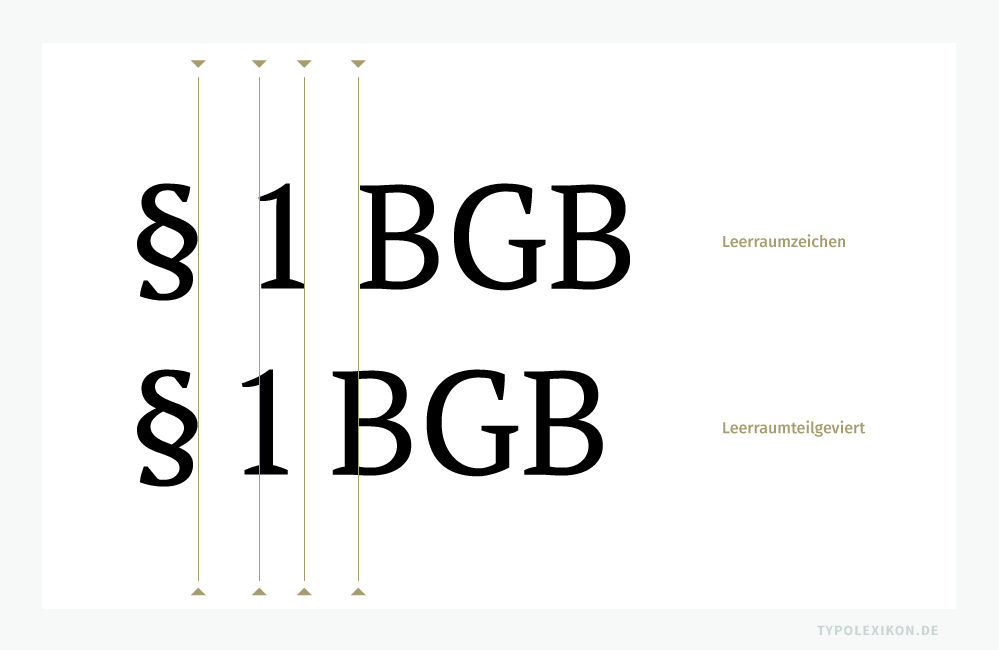
In professioneller Desktop Publishing Software gibt es dafür rund ein halbes Dutzend bereits abgestimmter Leerraumgevierte nebst spezieller Ziffernleerzeichen oder Interpunktionsleerzeichen, die einfach über ein Menü oder eine Tastenkombination eingefügt werden können. Zudem kann ein Leerraum durch Spationieren und Unterschneiden noch individuell ausgemittelt werden, was insbesondere im Akzidenzsatz oder bei Headlines sinnvoll sein kann.
Welches Teilgeviert das Richtige ist, ist abhängig
- vom Satzsystem
- von Schriftart und Schriftstil
- von der/den Ziffer/n (z.B. Mediävalziffern, Majuskelziffern, Kapitälchenziffern und/oder Tabellenziffern)
- von der Formgebung der Ligatur
- von der Normalschriftweite bzw. dem Kerning
Sinn und Zweck dieser mikrotypografischen Verfahrensweise ist es, einen ästhetisch optimalen Zeichenabstand zwischen Paragrafzeichen und Ziffer bzw. Buchstabe zu formen, der nicht zu eng (keine Kontamination), aber auch nicht zu weit (kein Loch – kein Gießbach) ist und der harmonisch mit dem Zeichenabstand vor und nach dem Paragrafzeichen korrespondiert – also schlussendlich die Schriftsatzästhetik und den Leseprozess (siehe auch Lesbarkeit) optimiert.
Bei OpenType Fonts gibt es heute unterschiedliche Glyphen von §-Ligaturen, die vereinzelt auch über eine optimierte Vor- und Nachbreite bzw. Dicktenkompatibilität zur nachgestellten Ziffer (bzw. Buchstabe) verfügen und somit nicht gegliedert oder im Feinsatz ausgeglichen werden müssen.
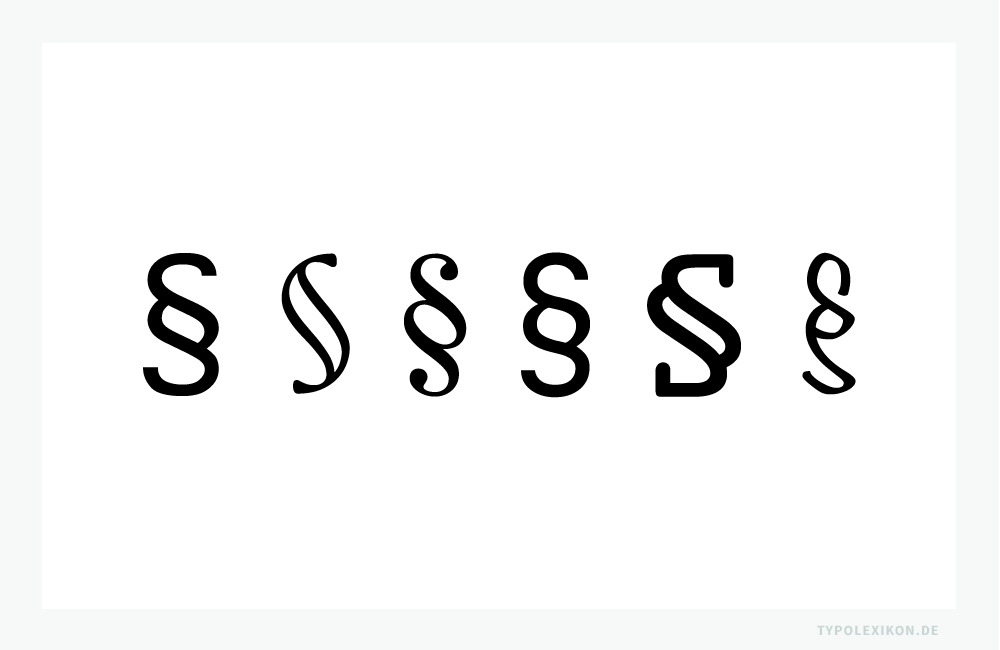
Historie
Etymologisch rührt das Substantiv »Paragraf« (13. Jh.) vom mhd. »Paragraf« für »Zeichen, Buchstabe« von spl. »paragraphus« für »Zeichen, dass »die Trennung im Text markiert« aus gr. »parágraphos« für »Trennungslinie« aus gr. »paragráphein« für »danebenschreiben«, aus gr. »gráphein« für »schreiben« und gr. »para«, also im Sinne von »das danebengeschriebene, hinzugefügte Zeichen«.